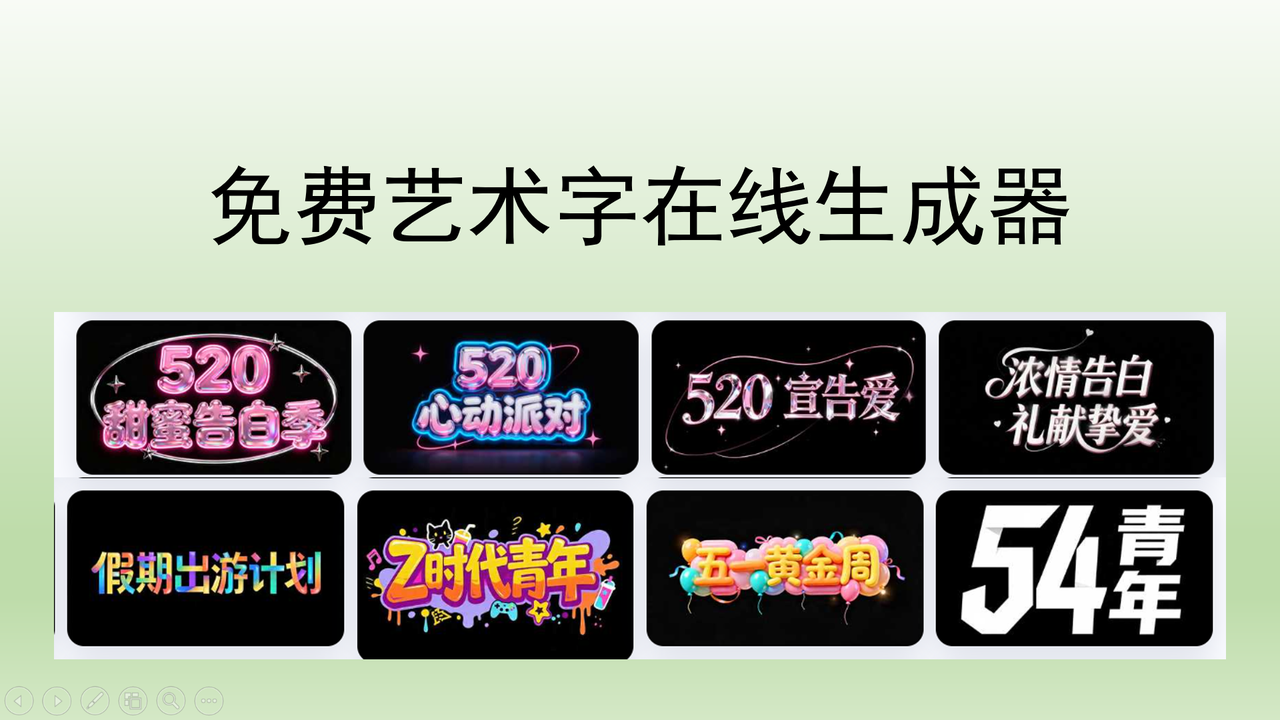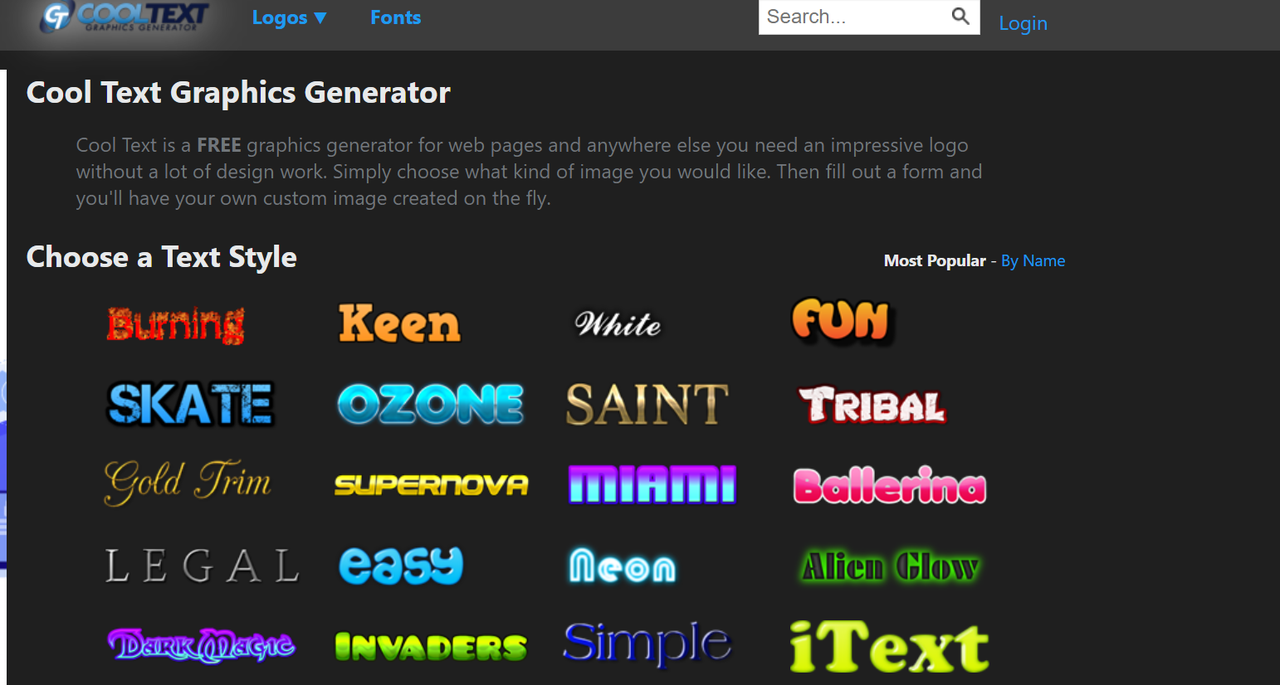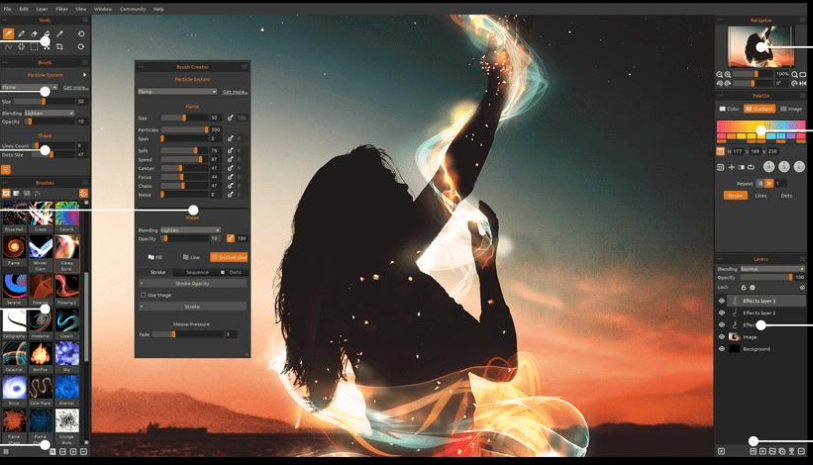
免费艺术字在线生成器:中文 / 英文特效字体,30 秒出图
选择一款好看的艺术字能够有效提升作品的设计感,还能快速抓住其他人的眼球。不管你是需要立体特效字、涂鸦风字体,还是渐变发光字体等等,市面上的艺术字在线生成器都能快速获得字体。本文整理了 5 个免费的艺术字在线生成器,支持生成中文/英文特效字体,30s 即可出图,零门槛打造艺术字的精美效果!比起从零开始自己设计字体,这些工具无需安装、无需掌握设计技巧,只需要在线一键生成同款艺术字,简直就是手残党的福音!对于很多资深设计师来说,这些艺术字在线生成器也大大提升了他们的工作效率。
一、字由
要说在线生成艺术字,我首选推荐字由,这是一款面向设计师用户提供字体应用,管理,授权服务,支持在 PS、AI、Sketch、CDR 等设计软件中一键应用字体,并提供 AI 识字、字体特效等实用设计工具,注册用户超 2000 万,是设计师必备的字体管理神器。很多人提到字由的第一反应都会是它收录了超多正版免费商用字体资源,而我们今天要重点聊得是 AI 字体功能。
简单来说,这个功能就是选择字体模板,一键同款相同字体效果。操作流程就是进入字由的“AI 字体”功能页面,从中国风、科技感、电商促销、涂鸦风等上百种预制模板中挑选你喜欢的一款;点击“做同款”,输入你要生成的文字内容;等待 10s 左右就会获得同款艺术字。而且可以直接透明背景的 PNG 格式图片,放进其他设计软件里直接就能用,是不是超级方便!除此之外,字由还提供了“字体特效”工具,可以为文字添加浮雕、光影等字体效果,让你的文字创作更具吸引力。
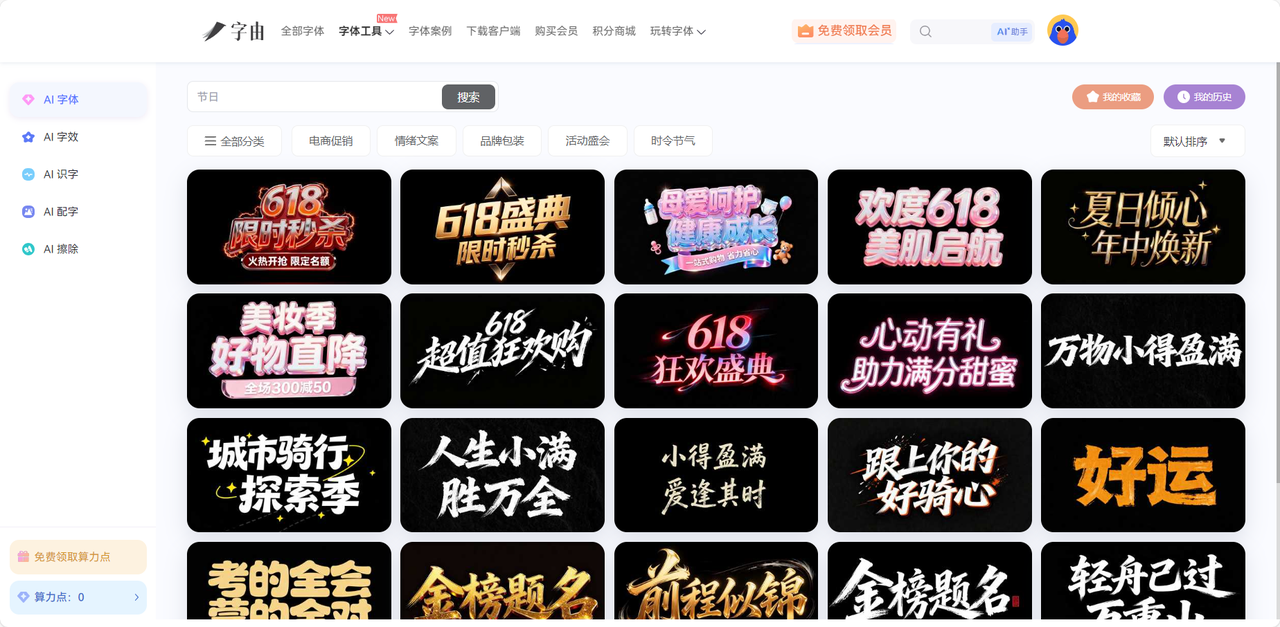
二、Cool Text
Cool Text 是一个相当老牌的免费艺术字在线生成器,在设计师圈子里一直都有不错的的口碑。它提供了几十种绚丽的文字特效,例如金属质感、晶莹玻璃质感、霓虹灯效果、发光立体效果等等,绝对会让你挑的眼花缭乱。我个人的使用体验来讲,Cool Text 的特效库比较偏向欧美潮流风,适合用来打造视觉冲击力强的标题字,用在品牌推广、线下促销等场景里能迅速吸引其他人的目光。值得一提的是,Cool Text 有批量生成功能,输入想要的文字内容之后,你可以选择一次性生成多个不同特效的版本,便于对比选择最心仪的艺术字效果。不仅如此,这款工具还支持自定义颜色、字体大小、阴影程度等细节方面,用户自由度还是蛮高的。唯一需要留意的一点,Cool Text 的艺术字主要以英文为主,中文字体的兼容性一般,输入汉字很难匹配出完美的视觉效果。
三、Flame Painter
与传统的免费艺术字在线生成器不同,Flame Painter 本质上更像是一款渲染功能强大的在线绘画工具。它的核心特色功能就是火焰画笔,用户可以像画画一样,通过它内置系统画出想要的艺术字,生成极具艺术感的火焰、光晕、星云、流光等效果的字体,看起来就像是文字本身在燃烧的那种感觉,追求新奇艺术字效果的小伙伴,可以亲自体验感受一下这款工具的魅力。
据很多设计师朋友们的评价来说,Flame Painter 比较擅长用来制作流光溢彩的艺术字,非常适配电竞主题活动、音乐节海报标题、派对宣传图等场景。因为它内置了多种粒子画笔,用户可以自由调整画笔颜色、大小以及流动速度,无论是制作静态的艺术字,还是动态的艺术效果,Flame Painter 都能呈现出相当高级且与众不同的视觉质感,是非常好的帮手。
四、Textcraft
接下来要给大家推荐的是 Textcraft ,这是专为像素风格爱好者和游戏玩家打造的乌托邦,最早它就是用来制作类似“我的世界”等像素游戏风格的立体艺术字以及图标。我上次尝试了一下,不得不说 Textcraft 对于像素风格研究很透彻,生成的文字自带块状质感,色彩饱满且笔画边缘硬朗,完美还原了像素游戏时代的怀旧感。
生成艺术字的过程也非常简单,你只需要输入任意文本内容,在纹理库里选择一个喜欢的材质(钻石、石头、草地等),再用滑块调整一下厚度以及阴影方向,还可以添加发光特效哦,最终就可以直接导出为PNG格式图片啦。整个过程无需任何设计经验,且免费版 Textcraft 就完全可以实现,足够应付你的日常设计需求。如果你是专攻游戏领域的设计师,或是正在运营游戏类自媒体账号,收藏这款工具是最佳选择!
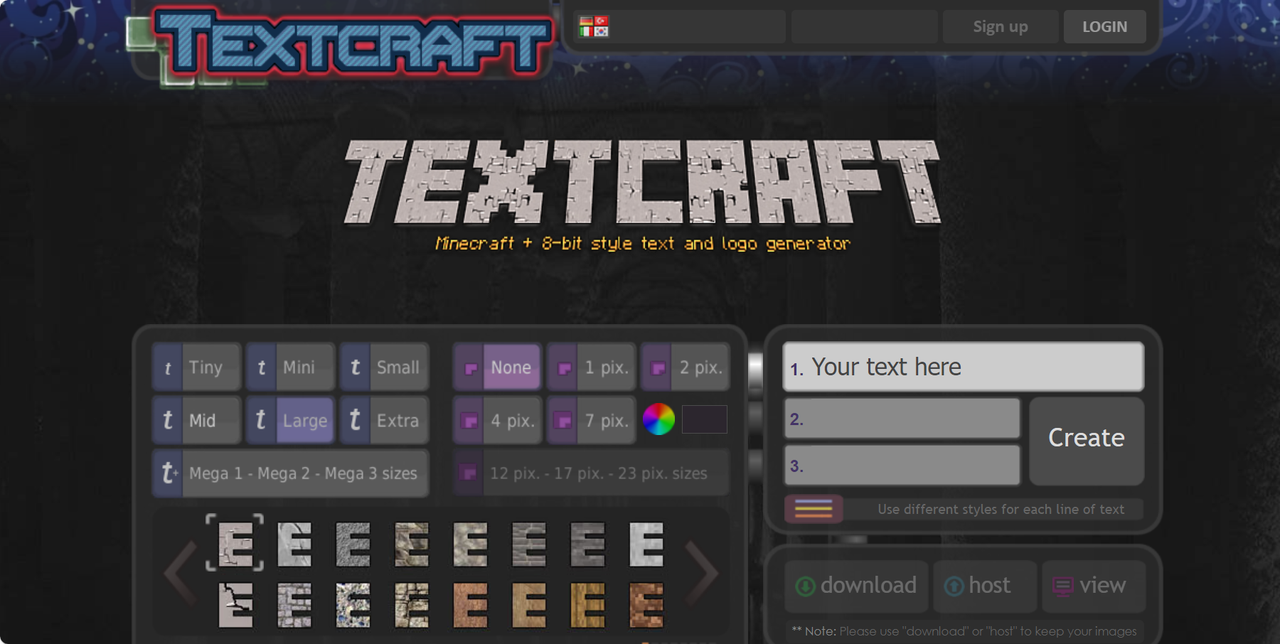
五、Carat AI
Carat AI 是一个基于 AI 模型的免费艺术字在线生成器,它最大的亮点就是对话式交互界面,也就是说你可以直接向它提出自己的需求,AI 会自动生成符合要求的艺术字。目前为止,Carat AI 已经继承了 30 多种 AI 模型,业内领先的模型几乎这里都有,能够帮你快速生成富有艺术感的气泡风、涂鸦风或立体风字体。如果不满意第一次生成的效果,你还可以通过对话来修改生成字体的颜色、笔画等细节,整个过程比较像是你作为老板给它下达命令,它会自动修改,无需你手动调整字体参数。